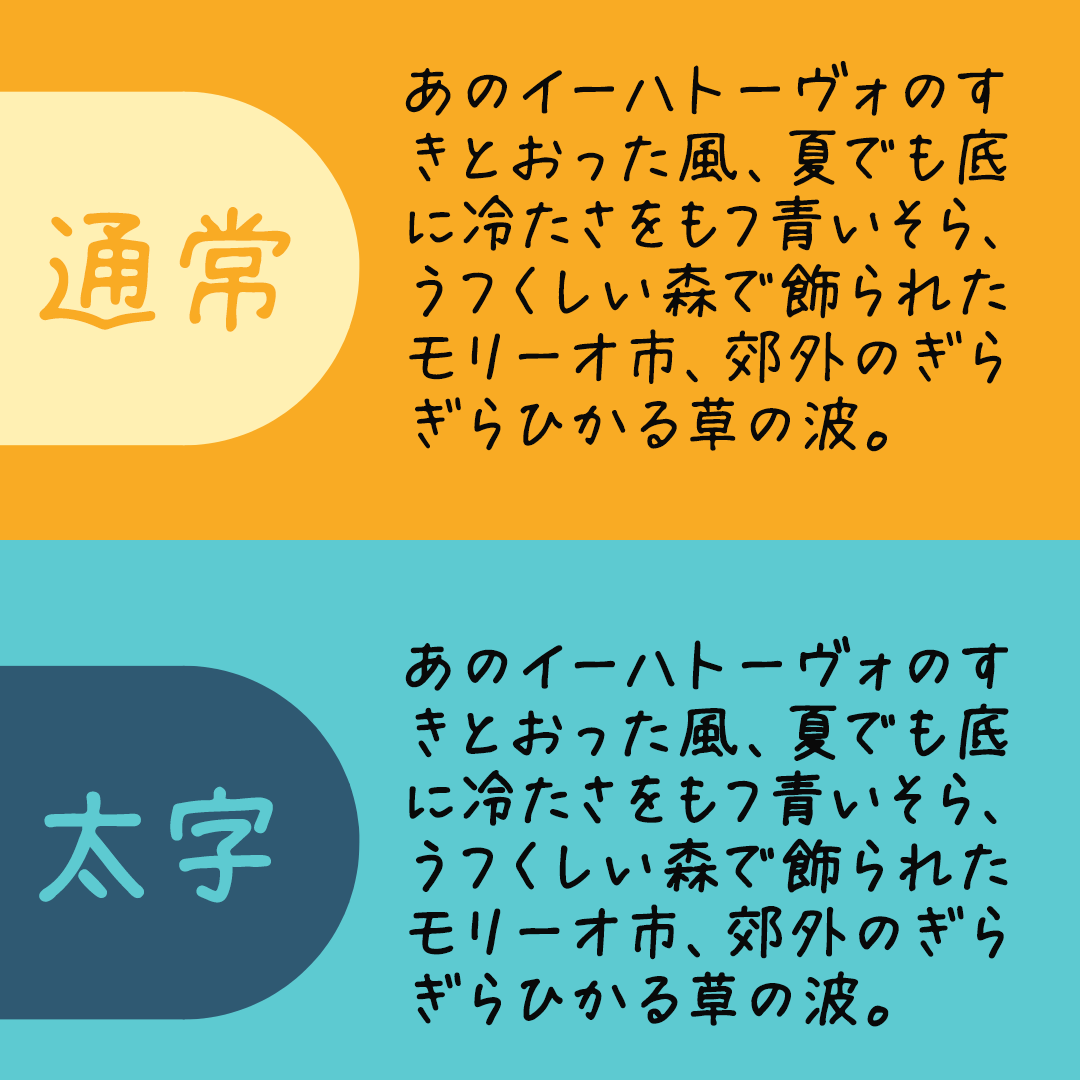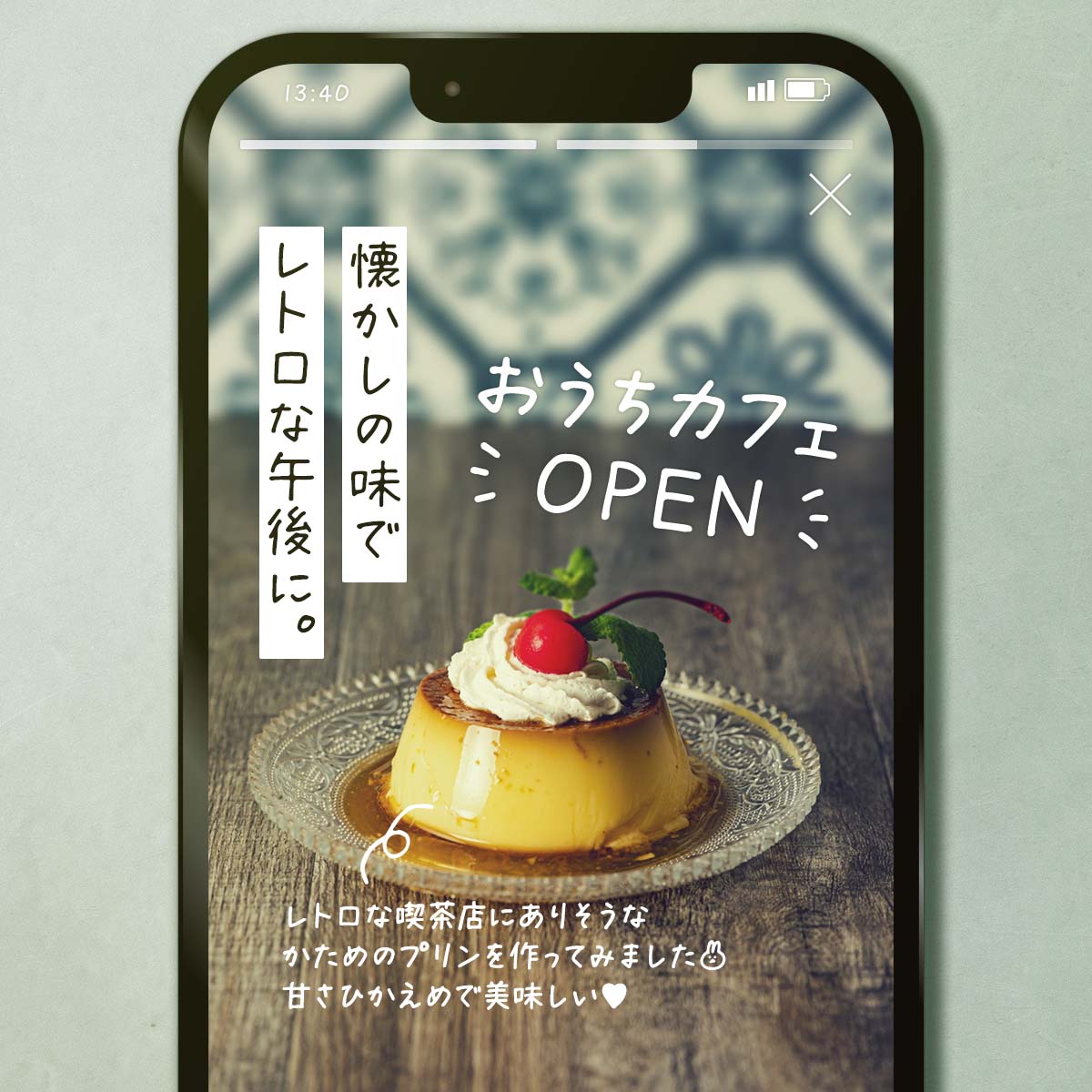
まちのてちょう
まちのてちょう:手書きの温かみをデザインに
「まちのてちょう」は、温かみのある手書きの風合いと高い可読性を兼ね備えたフォントです。
標準的な太さの「まちのてちょう」と、少し太めの「まちのてちょう Bold」の2種類があり、デザインに応じた使い分けが可能。背景写真やSNS投稿にも自然に溶け込み、縦書きでも美しく整います。オリジナルの絵文字や記号も豊富で、創作活動の幅を広げます。
「まちのてちょう」の特徴
1. 2つの太さのバリエーション
まち@machicooooo まちのてちょう 2つの太さ
「まちのてちょう」は、ラインナップに通常とBoldの2つのバリエーションをご用意。デザインのテーマや利用シーンに応じて使い分けることができます。
標準的な太さの「まちのてちょう」は長文でも読みやすく、少し太めの「まちのてちょう Bold」は強調したい見出しやメッセージに適しています。
2. フラットで可読性に優れたデザイン
まち@machicooooo まちのてちょう 可読性に優れたデザイン
手書きフォントはデジタル画像や背景写真と組み合わせるのが難しいこともありますが、「まちのてちょう」シリーズは自然な手書き感と絶妙なバランスを実現。SNSの投稿写真やサムネイルのアクセントとしてもピッタリです。
3. 縦書きも横書きも見やすいデザイン
まち@machicooooo まちのてちょう 縦書きも横書きも見やすい
「まちのてちょう」シリーズは、長文でもはっきり読みやすい設計。基本的には横書きに利用することを目的としたフォントですが、縦書きも想定して一部縦書き対応記号を収録。縦書きにも十分に利用できます。
4. 第二水準漢字&オリジナル絵文字&記号も多数収録
まち@machicooooo まちのてちょう 第二水準漢字&オリジナル絵文字&記号
「まちのてちょう」シリーズは、JIS第一水準・JIS第二水準・IBM拡張文字の漢字を収録した、実用性ばっちりの手書きフォント。「はしごだか (髙)」「立つさき (﨑)」などのこだわりたい文字や、「龜・學」のようによく使う旧字も使えます。
また、「ろしあもじ」「ゆうびん」「でんわ」「じす」「やじるし」と入力・変換すると、オリジナルの絵文字や記号が豊富に表示され(※)、デザインのアクセントとして活用可能。創作活動やSNS投稿の写真にも馴染み、個性的で魅力的な表現を演出できます。
「まちのてちょう」の活用シーン
日常的なSNS画像
まち@machicooooo まちのてちょう 使用例
創作活動
まち@machicooooo まちのてちょう 使用例
フォントブランド「まち@machicooooo」からのコメント
フォントを作り始めたきっかけ
「あなたの文字、ちょうどいいからフォントにしてほしい」と言われたのをきっかけに、手書きした文字からフォントを作り始めました。
フォント作りのポリシー、意識していること
「身近な誰かが、残してくれた書き置き」がコンセプト。ついつい読み込んでしまうような、手書きのあたたかさを追求しています。